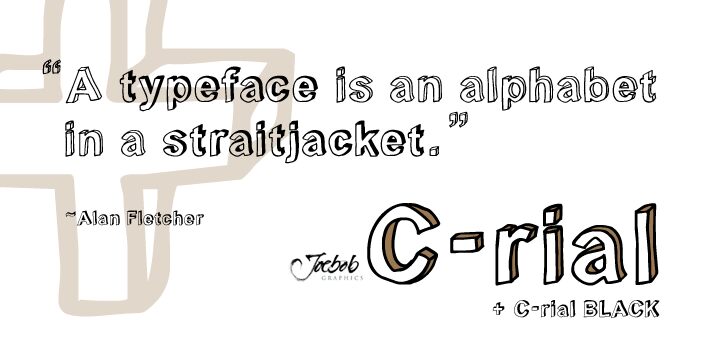
C Rial Black, stworzony przez J O E B O B graphics, to darmowy font displayowy 3D w stylu kreskówkowym, wyróżniający się żywymi, ręcznie rysowanymi formami i głębokim, przesuniętym cieniem. Nieregularne kontury, pochylone krawędzie i nierówne proporcje nadają literom energetyczny charakter wycinanki z papieru lub tytułów komiksowych w stylu retro.
Trójwymiarowa sylwetka wprowadza zabawny ruch do logotypów gier, okładek książek dla dzieci, opakowań przekąsek i plakatów wydarzeń. Ten darmowy font może również nadać animowanym napisom tytułowym i brandingowi inspirowanemu komiksami energiczny, ręcznie wykonany charakter, zwłaszcza gdy liternictwo musi ściśle współgrać z ilustracjami.